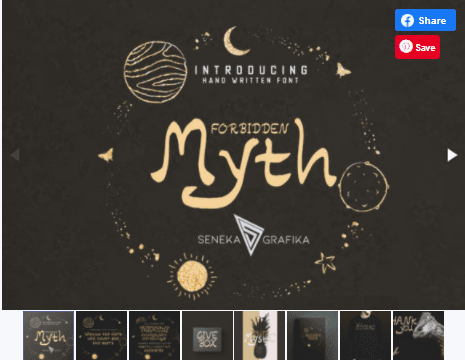
Forbidden Myth Font
Запретный миф - традиционная история, особенно касающаяся ранней истории людей или объясняющая какое-либо природное или социальное явление, обычно связанное со сверхъестественным существом или событием.
«Запретный миф» — это уникальный и простой рукописный шрифт. Он в основном подходит для неформальных проектов, таких как плакаты, открытки, личный брендинг и многое другое.